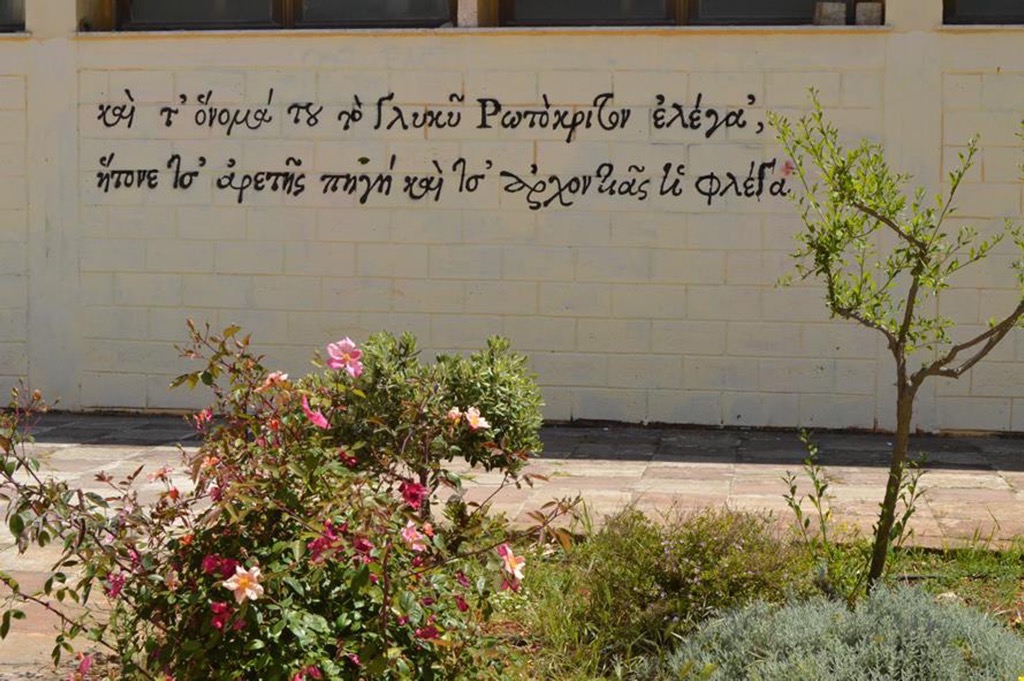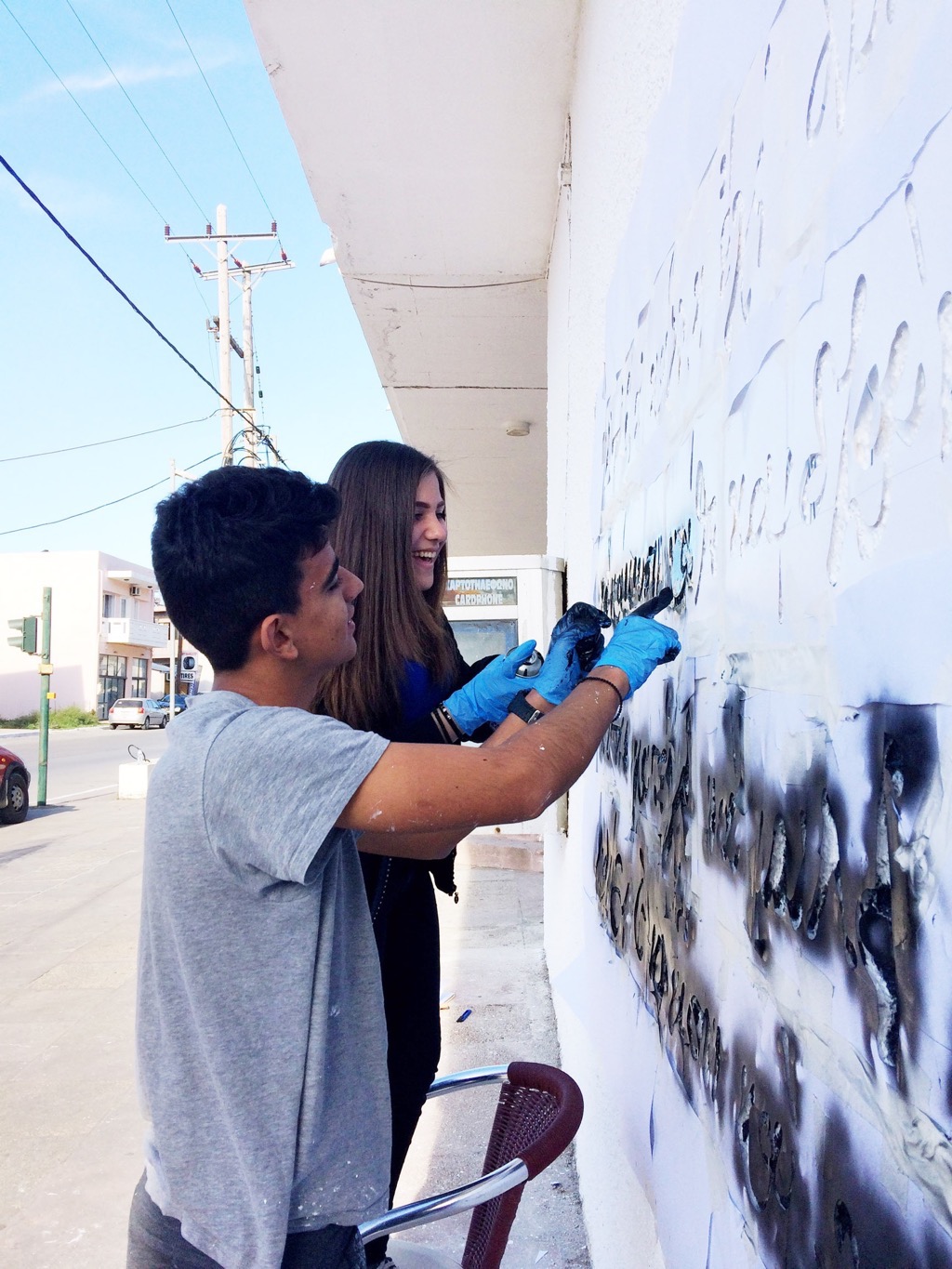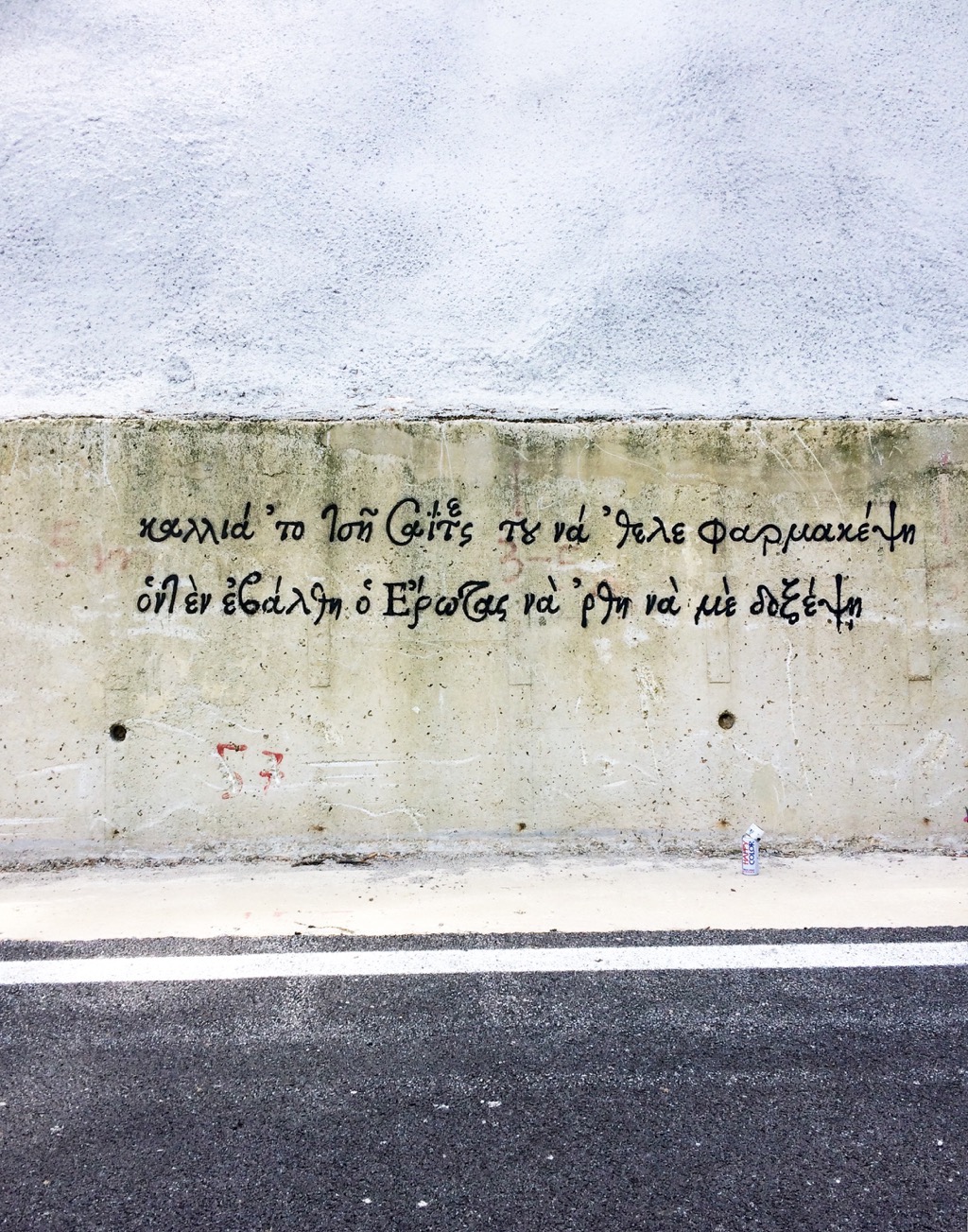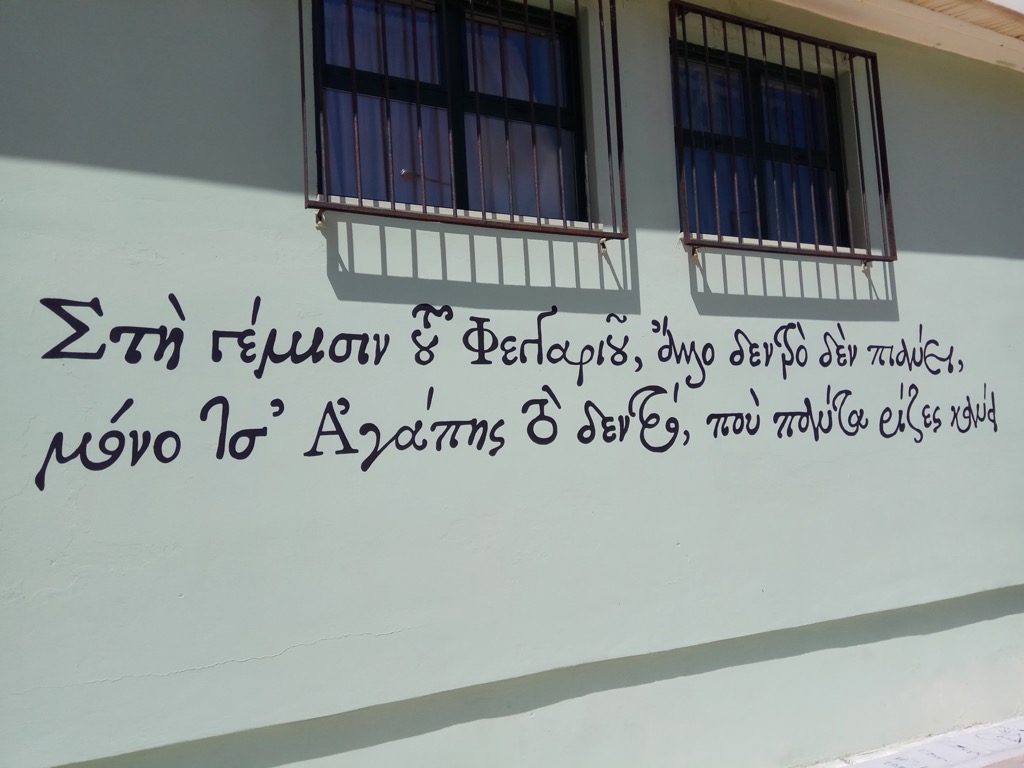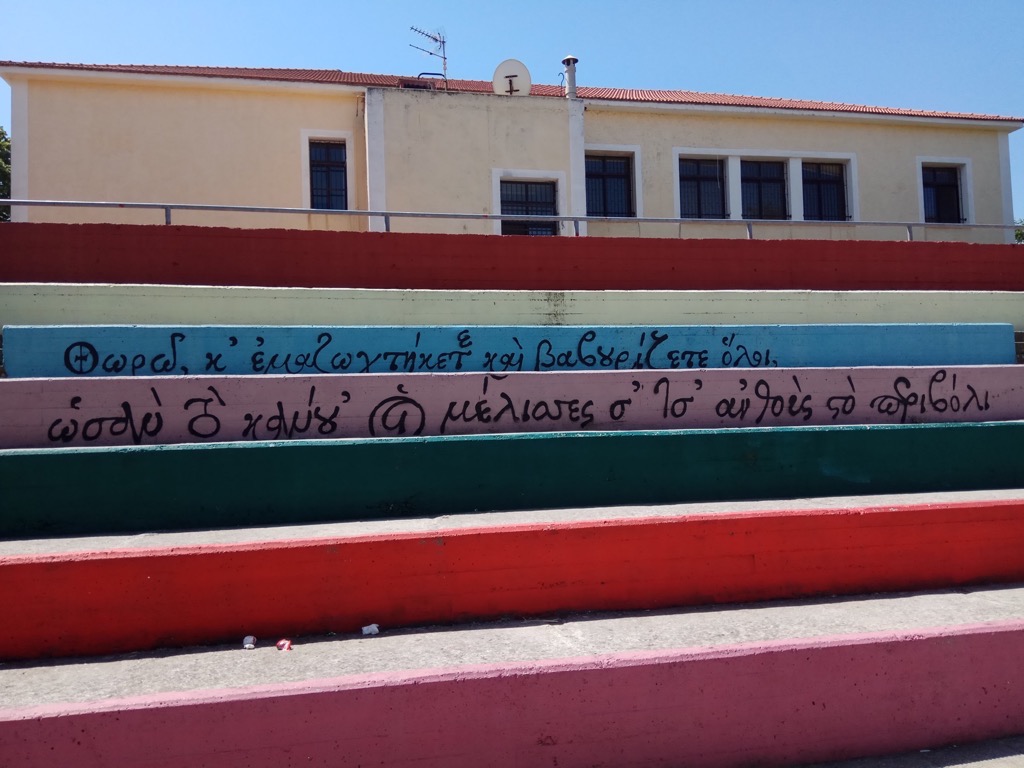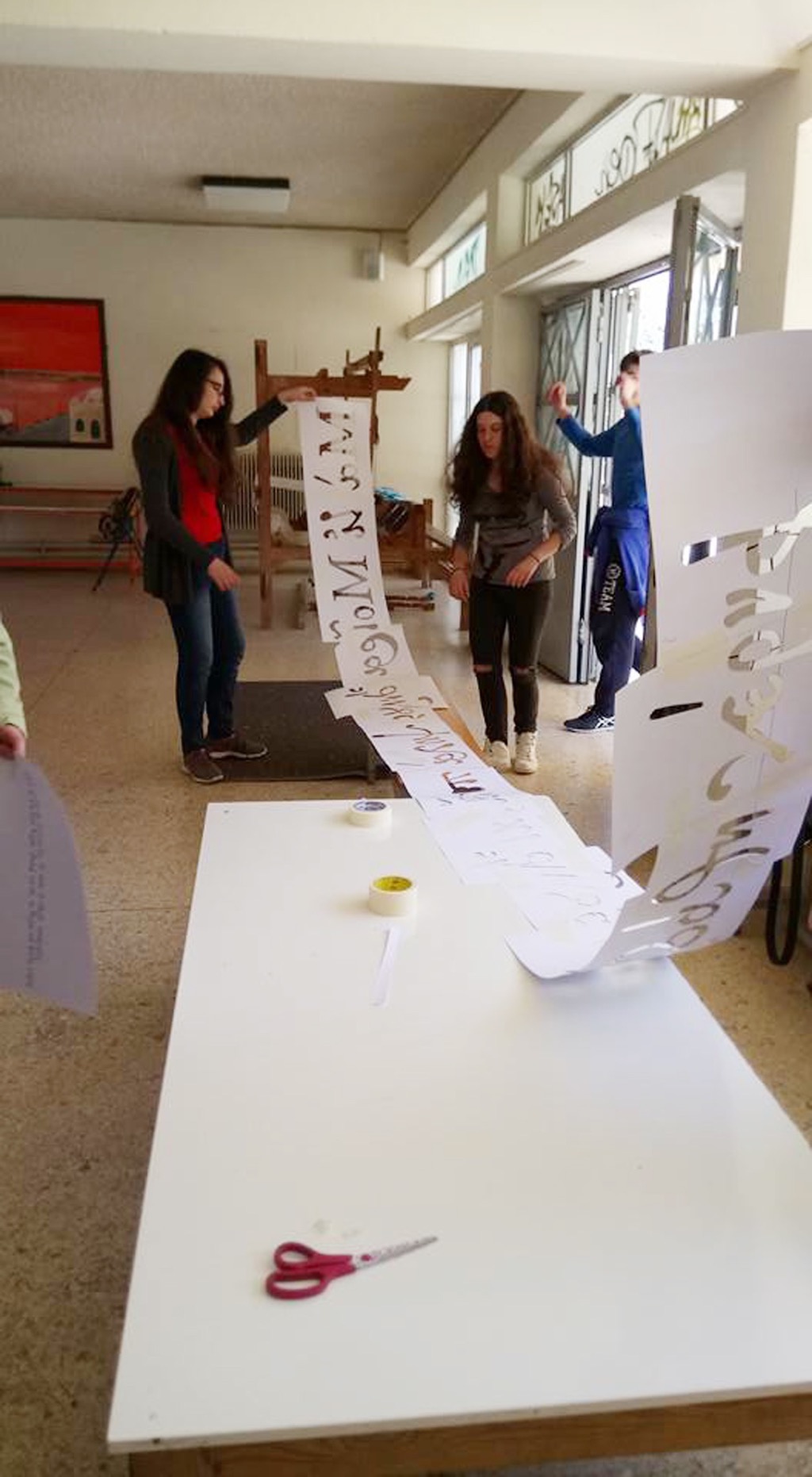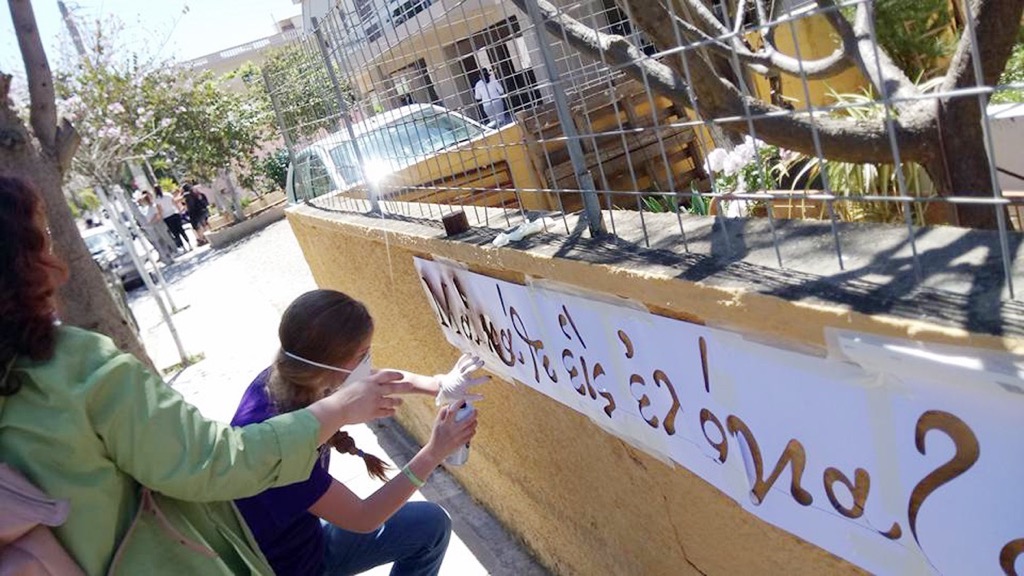
Με δίστιχα της Ερωφίλης και του Ερωτόκριτου “άνθισαν” μέσα στον Μάιο προαύλια σχολείων και δημόσιοι χώροι στα Χανιά και την υπόλοιπη Κρήτη, σε ένα νησί με παράδοση στην ποίηση και την καλλιγραφία. Πώς έγινε αυτό; Πρόκειται για το πρωτότυπο εκπαιδευτικό project “Η Τυπογραφία της Αναγέννησης συναντά την Κρητική Λογοτεχνία μέσα από την Τέχνη του Δρόμου” του Περιφερειακού Δικτύου που δημιουργήθηκε στην Κρήτη, στο πλαίσιο υλοποίησης Πολιτιστικών Προγραμμάτων Σχολικών Δραστηριοτήτων.
Στόχος της δράσης ήταν η ανάδειξη της πρώιμης Ελληνικής Τυπογραφικής Τέχνης και Καλλιγραφίας σε συνδυασμό με έργα της Κρητικής Λογοτεχνίας μέσα από τη σύγχρονη τέχνη του δρόμου. Συγκεκριμένα, οι μαθητές που ενεπλάκησαν στη συγκεκριμένη εκπαιδευτική δράση είχαν την ευκαιρία να εξοικειωθούν με την πρώιμη ελληνική τυπογραφική τέχνη, να προσεγγίσουν την κρητική λογοτεχνία του 16ου και 17ου αιώνα μέσα από σύγχρονες μορφές έκφρασης, όπως το γκράφιτι, σε μία διαδικασία που φιλοδοξεί να συμβάλλει στην ευαισθητοποίηση του ευρύτερου κρητικού κοινού.
Στο Περιφερειακό Δίκτυο συμμετείχαν η Διεύθυνση Δευτεροβάθμιας Εκπαίδευσης Χανίων με ομάδες εκπαιδευτικών και μαθητών Λυκείων όλης της Κρήτης σε συνεργασία με το Τμήμα Γραφιστικής της Σχολής Καλλιτεχνικών Σπουδών του ΑΤΕΙ Αθήνας και το Μουσείο Τυπογραφίας.
Το πρόγραμμα πραγματοποιήθηκε με αφορμή τη διεξαγωγή του 4ου Διεθνούς Συνεδρίου του Συνδέσμου Ευρωπαϊκών Μουσείων Τυπογραφίας (Association of European Printing Museums) που διοργανώνει το Μουσείο Τυπογραφίας και θα φιλοξενηθεί για πρώτη φορά στη χώρα μας, την ερχόμενη εβδομάδα από τις 11-13 Μαΐου στα Χανιά, όπου και θα παρουσιαστούν οι δράσεις των συμμετεχόντων σχολείων.
ΛΟΓΟΤΕΧΝΙΑ, ΤΥΠΟΓΡΑΦΙΚΗ ΤΕΧΝΗ ΚΑΙ ΓΚΡΑΦΙΤΙ
Σκοπός του εκπαιδευτικού αυτού προγράμματος όπως επεσήμανε ο κ. Γιώργος Ματθιόπουλος είναι οι μαθητές της Κρήτης να γνωρίσουν τη βυζαντινή γραφή μέσα από την απαράμιλλη ελληνική γραμματοσειρά Grecs du Roi, που φιλοτέχνησε ο επιφανής Κρητικός λόγιος και καλλιγράφος Αγγελος Βεργίκιος και χάραξε ο Claude Garamont για την αποκλειστική χρήση του βασιλικού τυπογραφείου της Γαλλίας στα μέσα του 16ου αιώνα στην έκδοση κειμένων της αρχαίας ελληνικής γραμματείας.
Σύμφωνα με τον κ. Ματθιόπουλο: «Λίγο αργότερα εμφανίζεται στην Κρήτη η πρώτη μεταβυζαντινή ποιητική άνθηση με κορυφαία έργα τον Ερωτόκριτο του Βιτσέντζου Κορνάρου και την Ερωφίλη του Γεωργίου Χορτάτση, η οποία σηματοδοτεί τις απαρχές της νεοελληνικής λογοτεχνίας. Η άμεση συνάντηση των δύο αυτών κορυφαίων κρητικών επιτευγμάτων, της καλλιγραφίας και της θεατρικής ποίησης, δεν επιτεύχθηκε εκδοτικά τότε για μια σειρά από ιστορικές συγκυρίες. Αυτή η εναλλακτική επαναγραφή της Ιστορίας επιχειρείται σήμερα με σύγχρονο όχημα την τέχνη του δρόμου, μιας διεθνώς καταξιωμένης μορφής εικαστικής έκφρασης και επικοινωνίας σε δημόσιους χώρους που προσφέρει οπτική πρόσβαση σε ένα ευρύτερο κοινό, και εκτελείται με μεγάλη ποικιλία τεχνικών και υλικών μέσων».
Ετσι, μαθητές μαζί με σπουδαστές από την Κρήτη στο Τμήμα Γραφιστικής επέλεξαν και στοιχειοθέτησαν δίστιχα από τα κείμενα της Ερωφίλης και του Ερωτόκριτου με τα οποία οι μαθητές των συμμετεχόντων Λυκείων είχαν φιλοτεχνήσει με ποικίλα υλικά (χαρτόνια, σπρέυ, ξύλο, κ.ά.) σε επιλεγμένους χώρους του σχολείου τους και με καθοδήγηση των υπεύθυνων καθηγητών με στόχο να προσεγγίσουν και να μελετήσουν τη βυζαντινή καλλιγραφία και την ελληνική τυπογραφία. Παράλληλα, οι μαθητές εντόπισαν χώρους στις πόλεις και στα χωριά της Κρήτης, όπου σε συνεννόηση με τις δημοτικές αρχές ξεκίνησαν να τους διακοσμούν με δίστιχα.
Η όλη δράση φωτογραφήθηκε από τα σχολικά συνεργεία κατά την προετοιμασία και την εκτέλεσή της και συγκεντρώθηκε σε μία ενιαία παρουσίαση από την ομάδα των σπουδαστών του Τμήματος Γραφιστικής για να ανακοινωθεί στα πλαίσια του 4ου Διεθνούς Συνεδρίου Ευρωπαϊκών Μουσείων Τυπογραφίας, που διοργανώνει το Μουσείο Τυπογραφίας στα Χανιά από τις 11-13 Μαΐου 2017.
Επιθυμία όλων είναι να συνεχιστεί αυτή η καλλιτεχνική δράση και τους επόμενους μήνες από περισσότερους εθελοντές στην Κρήτη και να επεκταθεί σε μεγαλύτερη κλίμακα που θα περιλαμβάνει και νέες εκπλήξεις.
«Εμπνεόμενοι από τις δυναμικές διεθνείς καλλιτεχνικές αναζητήσεις οι νέοι μας θα πρέπει να μάθουν πώς να τις μπολιάζουν με τον πλούτο της εντόπιας παράδοσης και έτσι να μεταφέρουν στο παρόν τα διαχρονικά επιτεύγματα του ελληνικού πολιτισμού» σημείωσαν οι διοργανωτές.
“Τυποτρόπιον” εν δράσει
Πολύτιμη ήταν η συμβολή της ομάδας φοιτητών γραφιστικής “Τυποτρόπιον” για την υλοποίηση του προγράμματος. Πιο συγκεκριμένα στο πρόγραμμα συμμετείχαν οι φοιτητές:
• Στα Χανιά: Δ. Μαρκάκη, Μ. Βλαζάκη, Ε. Σπαντιδάκη, Γ. Φραντζεσκάκης, Ο. Μπιτσάκη και Κ. Σταθάκη, Δ. Γεωργουδάκη (Τμήμα Ιστορίας και Αρχαιολογίας Ε.Κ.Π.Α.).
Αξίζει δε να σημειωθεί ότι μεταξύ των γκράφιτι που πρόκειται να δημιουργηθούν τις επόμενες ημέρες είναι -έπειτα από επιθυμία του Δήμου Χανίων- και αυτά στον τοίχο του Δημοτικού Κήπου και το Πάρκο Ειρήνης και Φιλίας όπως και έξω από τη Διεύθυνση της Δευτεροβάθμιας Εκπαίδευσης Ν. Χανίων.